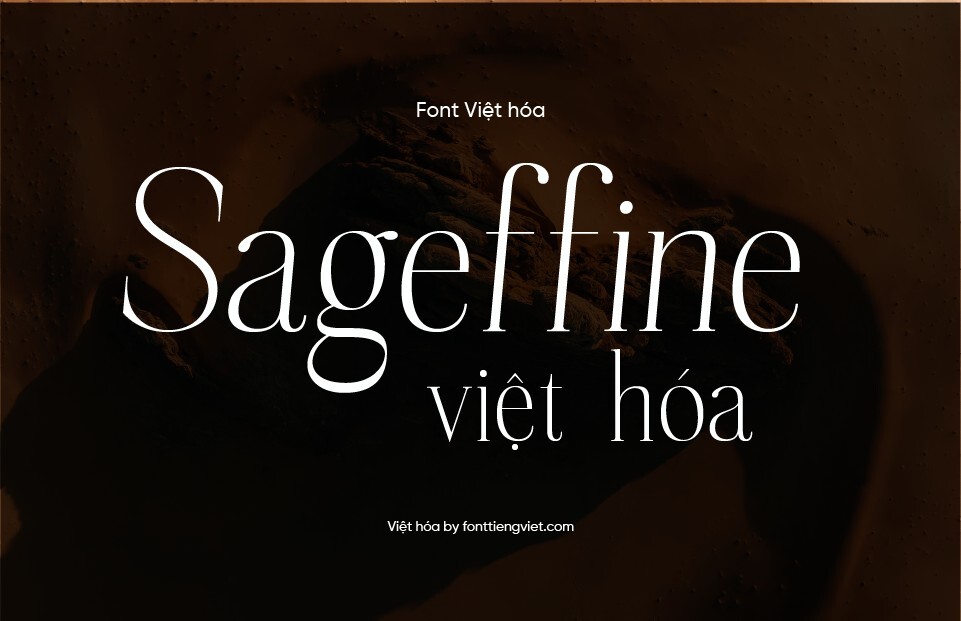
Font Việt hóa 1FTV VIP Sageffine
Font Việt hóa 1FTV VIP Sageffine – Lựa chọn đẳng cấp cho thiết kế hiện đại
Giới thiệu về Font Việt hóa 1FTV VIP Sageffine
Trong thế giới đồ họa chuyên nghiệp, việc tìm kiếm một bộ font vừa mang tính thẩm mỹ cao vừa hỗ trợ đầy đủ tiếng Việt là điều vô cùng quan trọng. Font Việt hóa 1FTV VIP Sageffine nổi lên như một giải pháp hoàn hảo, kết hợp giữa sự thanh lịch cổ điển và nét phá cách hiện đại. Đây là bộ font serif với những đường nét thanh mảnh, tinh tế, giúp tạo nên dấu ấn riêng biệt cho mọi tác phẩm nghệ thuật. Khi sử dụng Font Miễn Phí để sáng tạo, người dùng sẽ cảm nhận được sự mượt mà trong từng con chữ, giúp thông điệp truyền tải trở nên cuốn hút và chuyên nghiệp hơn bao giờ hết. Bộ font này được đội ngũ 1FTV chăm chút kỹ lưỡng, đảm bảo không lỗi dấu khi soạn thảo văn bản tiếng Việt.
Những đặc điểm nổi bật của Font Việt hóa 1FTV VIP Sageffine
Thiết kế Serif sang trọng và tinh tế
Đặc trưng lớn nhất của Font Việt hóa 1FTV VIP Sageffine chính là cấu trúc chân chữ (serif) sắc sảo. Các nét thanh và nét đậm được phân bổ hài hòa, tạo ra một nhịp điệu thị giác dễ chịu cho người đọc. Điều này đặc biệt hữu ích cho các bạn học sinh, sinh viên khi làm báo cáo hoặc các thầy cô giáo khi thiết kế giáo án điện tử, giúp nội dung trở nên trang trọng và dễ tiếp cận hơn. Font chữ này không chỉ đơn thuần là công cụ soạn thảo mà còn là một tác phẩm nghệ thuật thu nhỏ trên màn hình máy tính.
Khả năng ứng dụng đa dạng trong thực tế
Nhờ vẻ ngoài cao cấp, Font Việt hóa 1FTV VIP Sageffine thường xuyên được ưu tiên trong các dự án thiết kế logo, bộ nhận diện thương hiệu, bìa sách và thiệp mời sự kiện. Trong môi trường học đường, font này có thể dùng để trình bày các tiêu đề bài thuyết trình hoặc làm poster cổ động cho các hoạt động ngoại khóa. Tính linh hoạt của Sageffine giúp nó thích nghi tốt với cả định dạng in ấn lẫn hiển thị kỹ thuật số, giữ nguyên độ sắc nét ở mọi kích cỡ khác nhau.
Tối ưu hóa hiển thị trên các phần mềm đồ họa
Để phát huy tối đa vẻ đẹp của Font Việt hóa 1FTV VIP Sageffine, bạn nên kết hợp nó với các màu sắc trung tính hoặc tông màu pastel nhẹ nhàng. Trong các phần mềm như Adobe Photoshop, Illustrator hay thậm chí là Canva, người dùng có thể điều chỉnh khoảng cách giữa các chữ (kerning) để tạo ra bố cục cân đối nhất. Việc sử dụng font này cho các tiêu đề chính (Heading) sẽ tạo ra điểm nhấn mạnh mẽ, dẫn dắt ánh nhìn của người xem vào nội dung quan trọng nhất của trang giấy.
Lưu ý khi lựa chọn font chữ tiếng Việt
Kết luận về bộ Font Việt hóa 1FTV VIP Sageffine